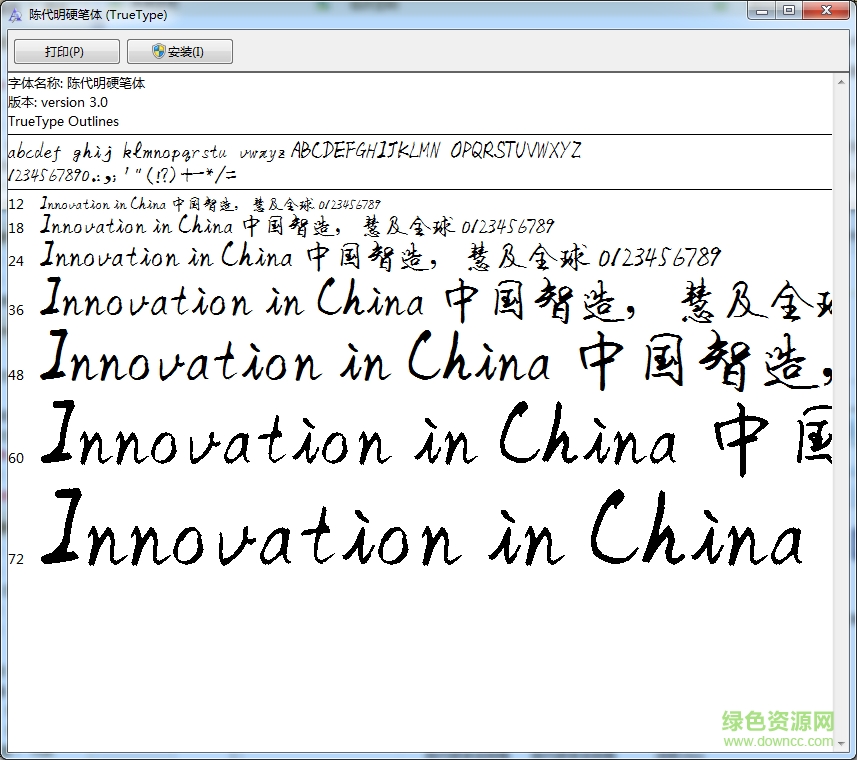
陳代明硬筆體
陳代明硬筆體是一款非常有個(gè)性的電腦字體,字體飄逸端正,適用于圖文印刷、美工創(chuàng)作、名片設(shè)計(jì)等領(lǐng)域,使用廣泛深受用戶喜愛??靵?lái)綠色資源網(wǎng)下載體驗(yàn)吧!
陳代明硬筆體字體介紹
陳代明硬筆體這款字體是真的很不錯(cuò),不僅字形特別美,還特別實(shí)用,可以用在很多方面。